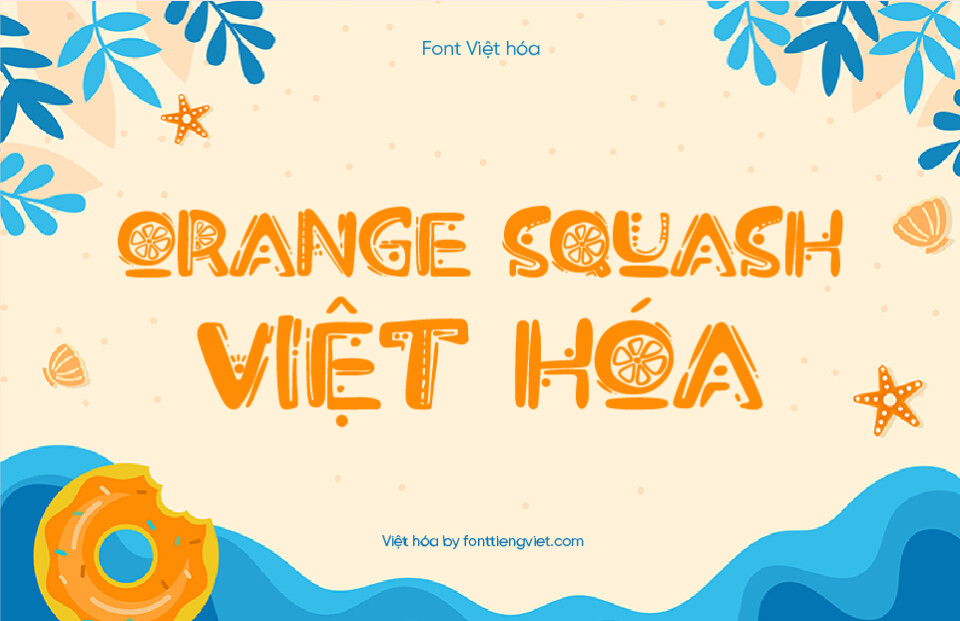
Font Việt hóa 1FTV Orange Squash
Giới thiệu về bộ Font Việt hóa 1FTV Orange Squash
Trong thế giới thiết kế đồ họa hiện nay, việc lựa chọn một Font Miễn Phí ấn tượng đóng vai trò quyết định đến sự thành công của sản phẩm. Font Việt hóa 1FTV Orange Squash là một lựa chọn hoàn hảo cho những ai yêu thích phong cách trẻ trung và năng động. Đây là bộ font chữ mang hơi hướng retro nhưng vẫn giữ được nét hiện đại, giúp các bạn học sinh và giáo viên dễ dàng tạo ra những bài thuyết trình hay báo cáo sinh động. Với đường nét dày dặn và uốn lượn tự nhiên, font chữ này gợi lên cảm giác vui tươi, phù hợp cho các chủ đề về lễ hội, thực phẩm hoặc các hoạt động ngoại khóa tại trường học.
Ưu điểm nổi bật của Font Việt hóa 1FTV Orange Squash
Khả năng hiển thị và tính tương thích
Font Việt hóa 1FTV Orange Squash đã được tối ưu hóa bảng mã tiếng Việt, giúp người dùng không còn lo lắng về lỗi gõ dấu hay hiển thị sai ký tự. Độ tương phản giữa các nét chữ giúp văn bản trở nên dễ đọc ngay cả ở kích thước nhỏ. Bạn có thể sử dụng font này trên nhiều phần mềm khác nhau như Word, PowerPoint hay Canva một cách mượt mà.
Ứng dụng đa dạng trong học tập và sáng tạo
Bộ font này đặc biệt hiệu quả khi dùng làm tiêu đề cho các tấm áp phích cổ động hoặc bìa sách bài tập. Sự phá cách trong từng nét chữ của Font Việt hóa 1FTV Orange Squash giúp khơi nguồn cảm hứng sáng tạo cho người xem, biến những nội dung khô khan trở nên hấp dẫn hơn bao giờ hết.
Kết luận về bộ font chữ độc đáo này